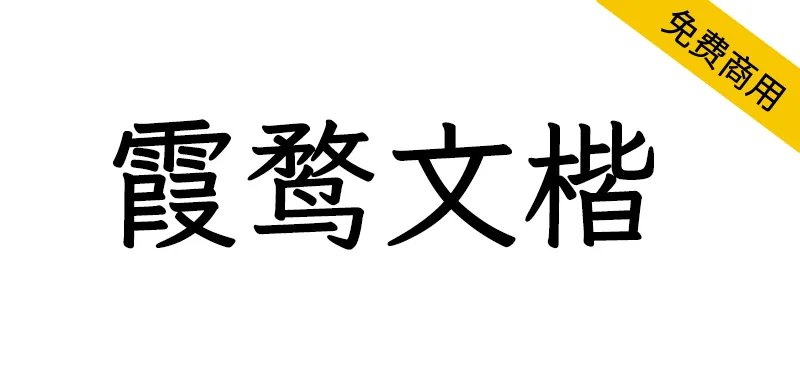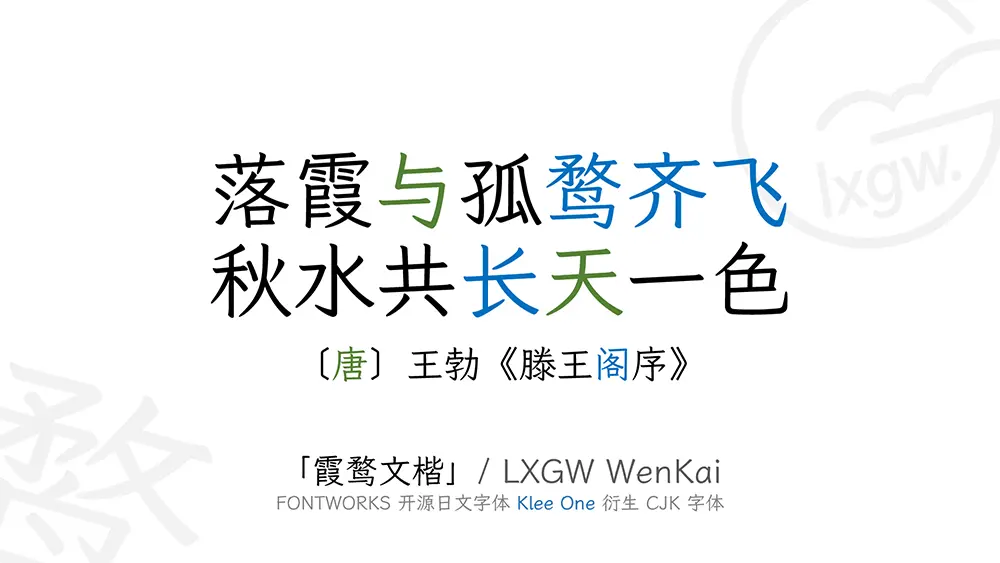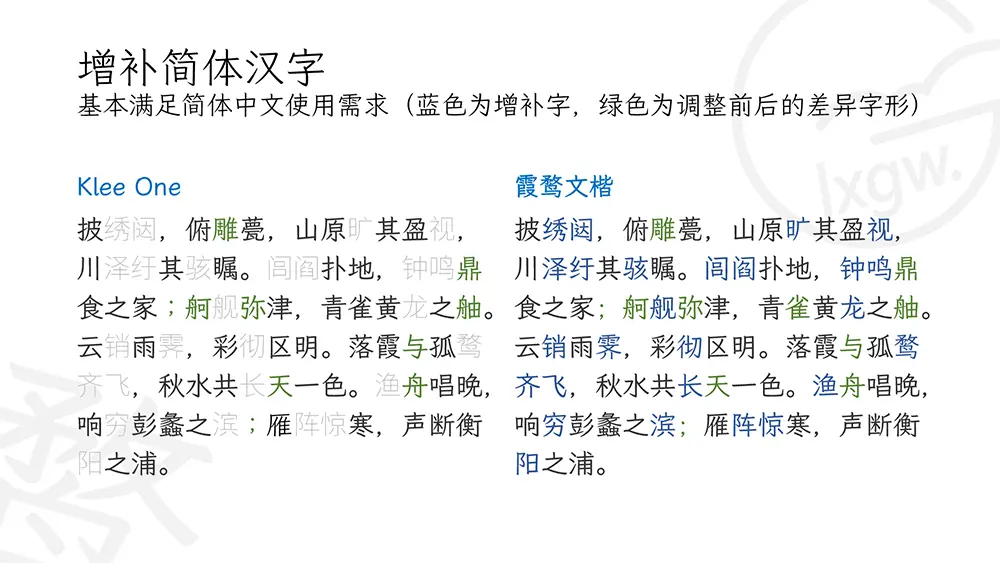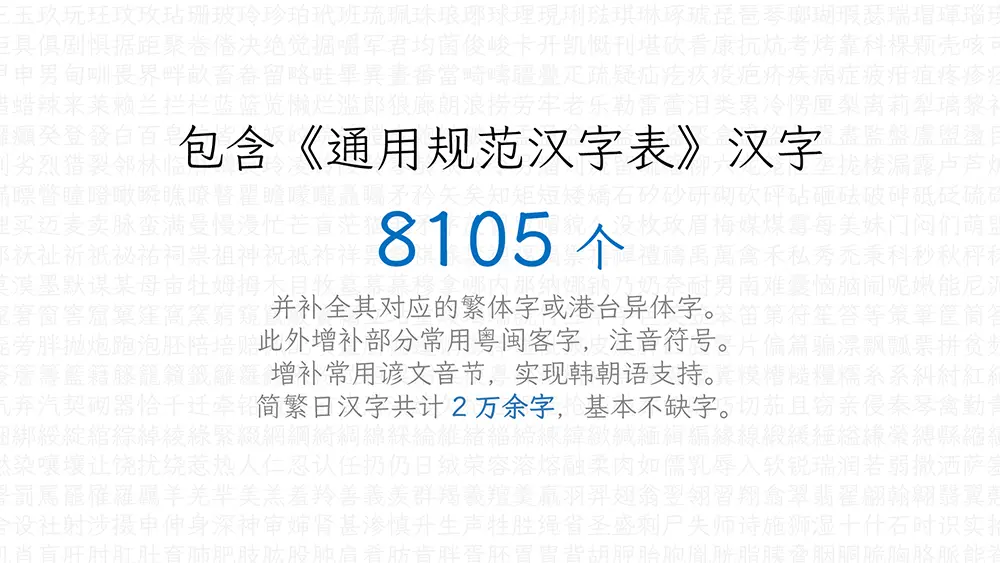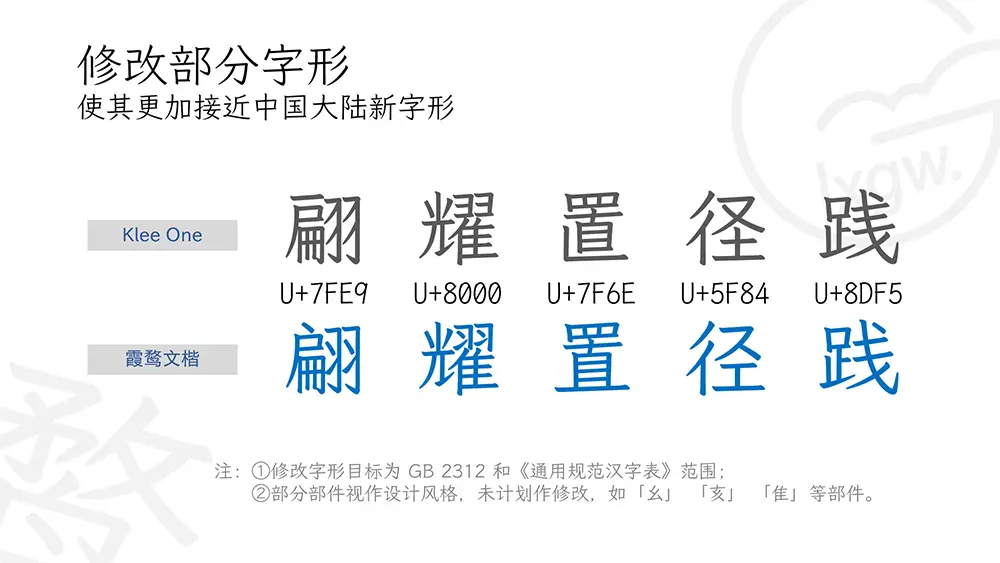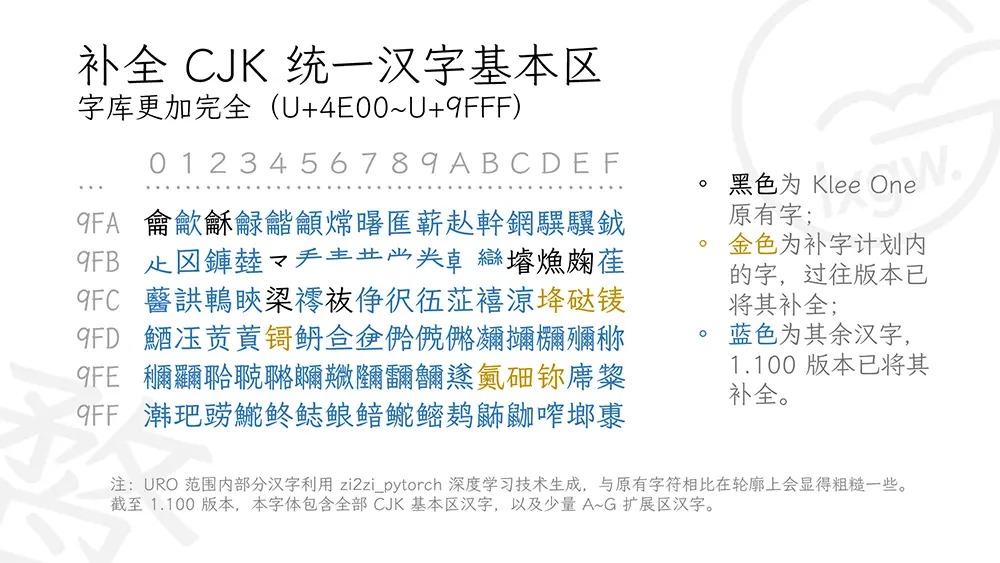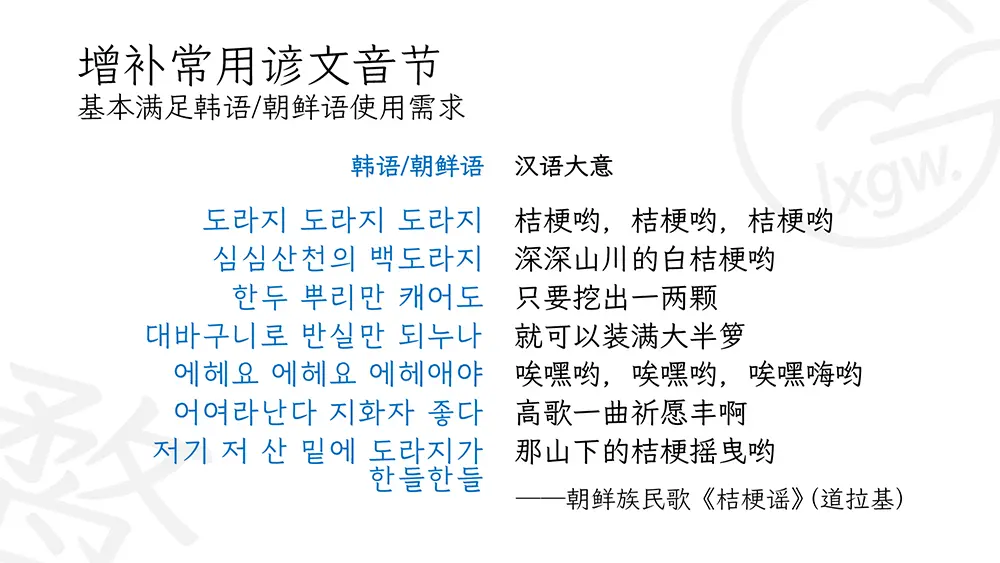
2020 年 12 月,日本著名字體廠商 FONTWORKS 在 GitHub 上發佈了 7 款日文字體,分別為 Train、Klee、Stick、Rock-n-Roll、Reggae、Rampart 和 DotGothic16,根據 SIL Open Font License 1.1 授權許可開源。7 款開源日文字體各有各的特點,而這 7 款字體中,字符數量最多的是 Klee。
這是一款有著日本教科書體風格的字體,兼有仿宋和楷體的特點。一些 DIY 字體愛好者曾先後用仿宋等字體補全這款字體,作為手機系統的美化字體移植在 iOS、Android 等手機系統中,受到很多玩機發燒友的歡迎。不過這樣補全的字體有一些不足之處。 第一,原有字體和後補字體之間有著一定的差異,致使一些不同的文字(如 Klee 原有漢字與後補簡體字)混排之後會有一定的違和感。 第二,由於補字所用的字體為商業版權字體,補全之後不可用於商業用途,還會有侵權的風險。此外,目前現有的開源中文字庫裡,楷體類寥寥無幾,仿宋類則幾乎沒有。
鑑於此,也為了豐富開源中文字體中的楷體門類,2021 年 1 月 20 日起,本人開始了為 Klee One 這一高質量的日文開源字體補全簡繁常用字的嘗試。因該字體具有一定的「文藝氣息」,命名 「霞鶩文楷」(其實當初是感覺這款字體適合正文閱讀定名「文楷」,後來發現這款字體可能並不太適合大段正文排版,相比之下更加適合詩詞之類的中等長度文本排版,或者註釋排版)。由於 Klee One 字體的 Regular 字重太細不太適合閱讀,選取原字體 SemiBold 字重作為 Regular 字重。經過長時間的積累,目前已發展成簡繁日韓均支持的 3 字重字體家族 (雖然拙劣粗糙了點) 。